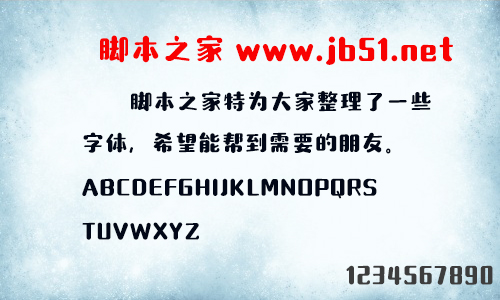
造字工房素白常規(guī)體是一款風(fēng)格圓潤的字體,素白體沒有僵硬的棱角,給人非常清新柔和的感覺,整體效果呆萌好看,歡迎到本站下載使用!
造字工房素白體字體是一款應(yīng)用于藝術(shù)設(shè)計(jì)方面的簡體中文字體,該字體筆畫粗壯,大字效果突出且引人注目;并且最大程度還原作者書寫字形,細(xì)節(jié)表現(xiàn)完整,且字庫完整,可以廣泛應(yīng)用于名片設(shè)計(jì)、新聞媒體、宣傳海報(bào)、ppt、影視制作以及內(nèi)容用字等領(lǐng)域。